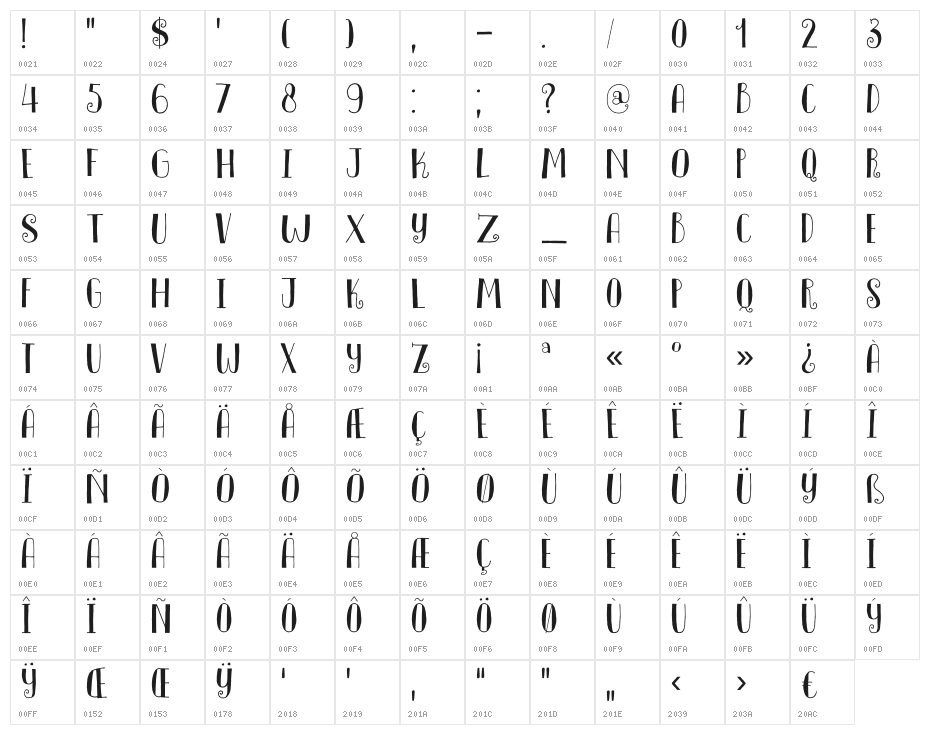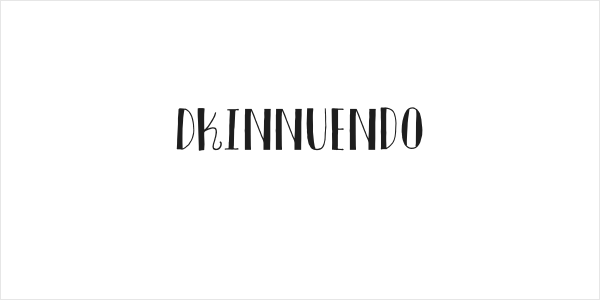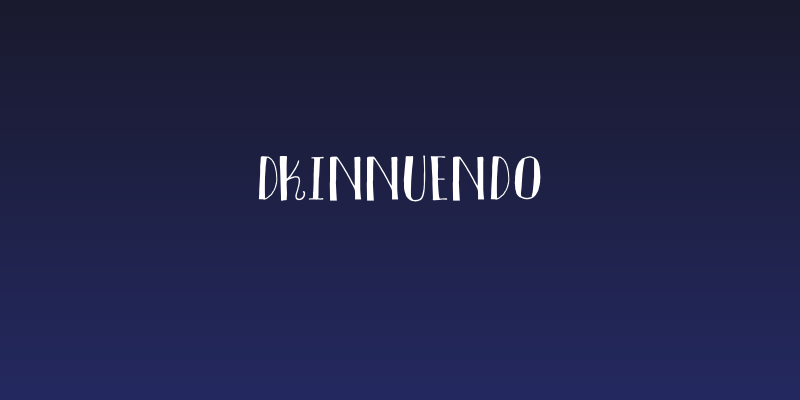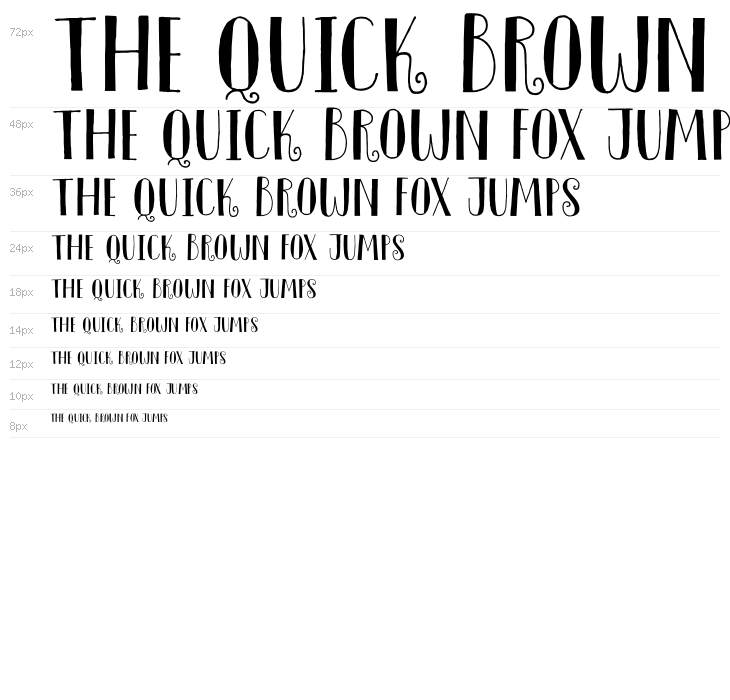
DKInnuendo Font
| Estilo general | Whimsical, Playful, Creative |
| Caso de uso | Headlines, Posters, Branding |
| Proyectos propuestos | Ideal for children's books, creative posters, playful branding, and whimsical invitations. |